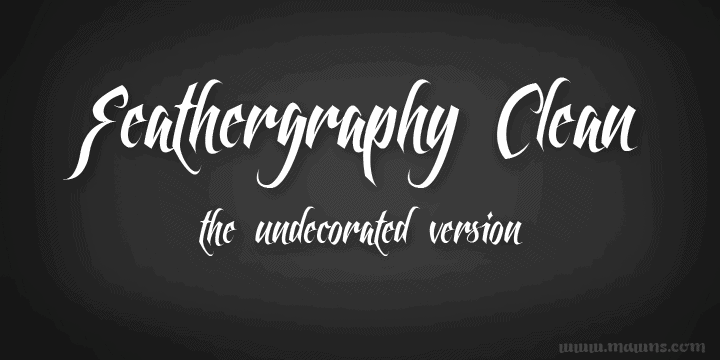
A fonte Feathergraphy Clean é uma escolha ideal para designers que buscam uma elegância discreta e uma tranquilidade visual perfeita, especialmente no meio do design de script. Criada pelo talentoso designer Hamilton, esta fonte oferece um ar natural e suave, perfeitamente adaptável a diversos projetos, seja em cartazes, letras de música ou qualquer outra aplicação onde desejaríamos transmitir uma mensagem com delicadeza e sutileza. Com sua tipografia leve e elegante, Feathergraphy Clean é perfeita para quem procura um equilíbrio entre simplicidade e expressividade. Suas linhas são finas, mas sempre se mantém legível e moderna, enquanto seu design suave evoca a sensação de frescor e pureza do vaporeto à medida que flui pelo papel. Fechar sua compra para o completo conjunto da fonte e uma licença comercial pode ser feito acessando o site oficial onde a font foi criada. Esta é mais que uma simples font: ela é um complemento versátil em seu arsenal de ferramentas de design. Obrigado por visitar nosso blog, aqui encontrará mais recursos de design para seus projetos futuros. Fechar sua compra direta no site oficial garantirá acesso a este e a muitas outras opções únicas do designer Hamilton.